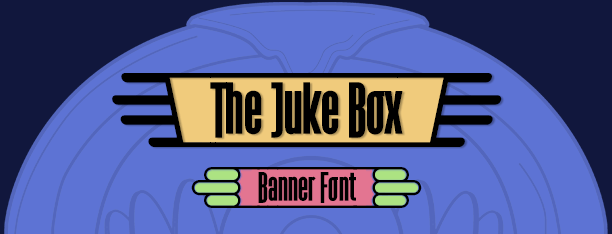
The Juke Box es un experimento tipográfico basado en mi anterior fuente La Babaca, la nueva tipografía ahora está inscrita en un marco que conforma una caja, para cerrar dicha caja la fuente dispone de 12 juegos de cierres de caja con estilo JukeBox años ’50.
(The Banner Font)
Estilo: Decorativa
Proporción: Regular
Glyphs: 545
Año de publicación: 2016.
Funciones OpenType: Additional languages, All Alternates, Contextual Alternates, Denominators, Extended Fractions, Historical Forms, Historical Ligatures, Inferiors, Kerning, Localized Forms, Numbers Small Caps, Numerators, Ordinals, Ornaments, Scientific Inferiors, Slashed Zero, Standard Ligatures, Subscript, Superiors, Superscript, Titling alternates.